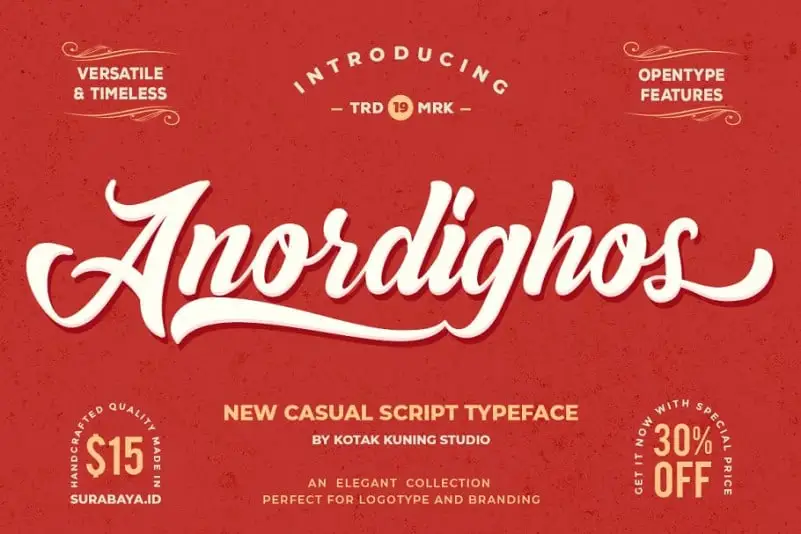
Anordighos Script Font – Fonte Grátis
Anordighos Script Font
Descubra a elegância do Anordighos Script Font, uma tipografia script moderna e sofisticada. Este tipo de letra é perfeitamente adaptado para trabalhos que valorizam um toque único e criativo. É ideal para aplicações como logotipos, design de produtos, rótulos, ícones na internet, roupas, convites, sinalização, clubes esportivos ou eventos especiais. Ideal tanto para designers profissionais quanto para iniciantes que buscam adicionar um toque pessoal e original aos seus projetos, o Anordighos Script Font combina a elegância do estilo script com a personalidade de uma tipografia escrita à mão. Este tipo de letra é perfeita para aqueles que desejam dar vida às suas ideias de design, seja em uma plataforma digital ou em um projeto físico. Ideal tanto para estilos formais quanto criativos, o Anordighos Script Font oferece flexibilidade e versatilidade. É fácil de usar em diversas aplicações e se adaptará perfeitamente a diversos projetos, sem perder sua personalidade única. Com ele na sua caixa de ferramentas de design, poderá expressar seu estilo e transformar seus projetos num verdadeiro ponto de referencia no mercado.